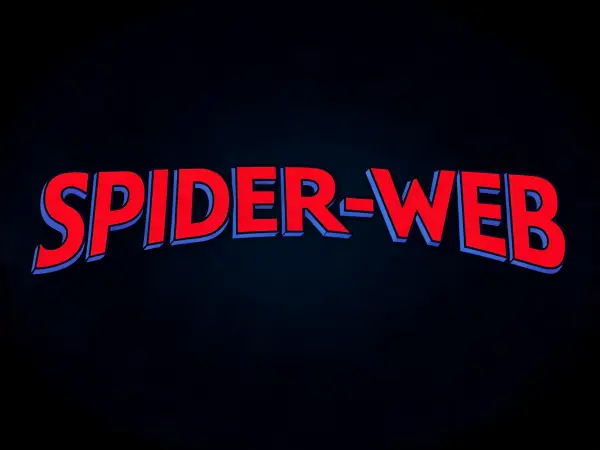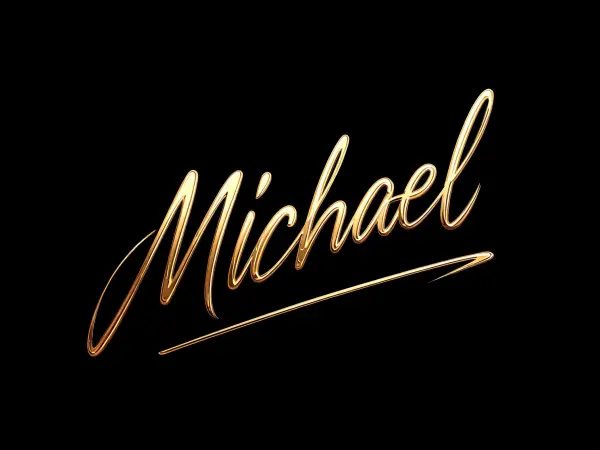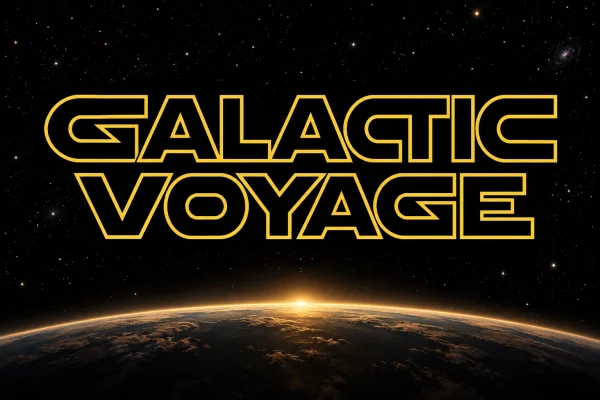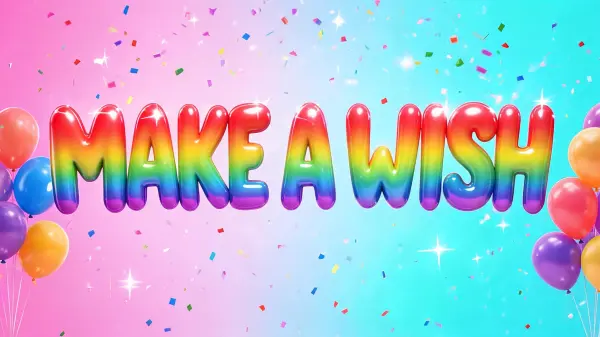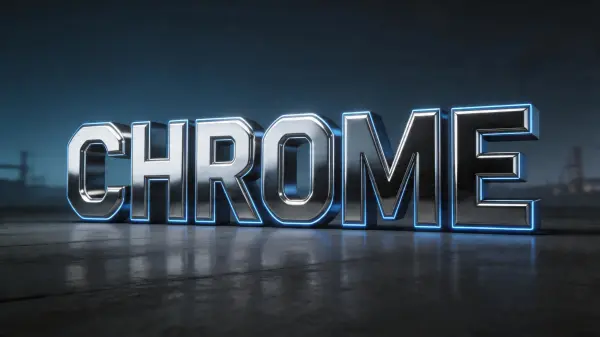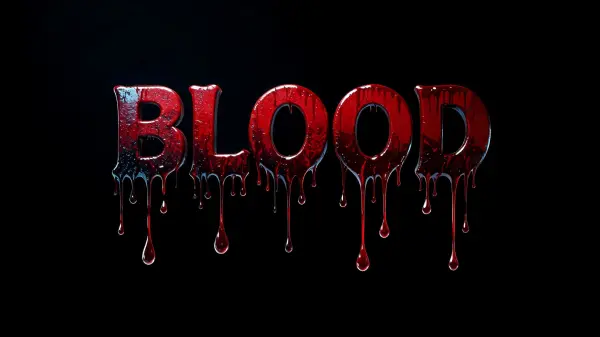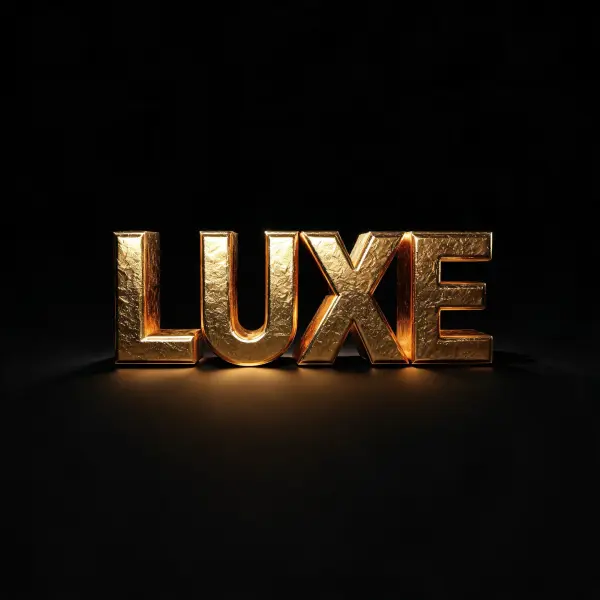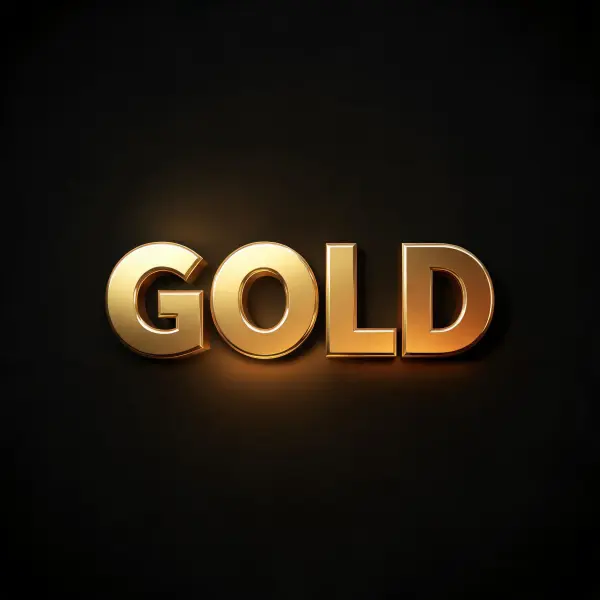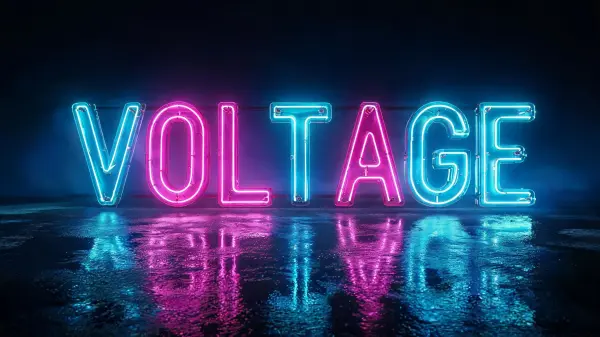
ข้อความหัวเรื่องบนโปสเตอร์
- พรอมต์หลัก
- ตัวอักษรทรงสูงแคบสีเงินปัดลาย ขอบคมชัด และเว้นระยะห่างระหว่างตัวอักษรมาก
- พรอมต์ฉาก
- พื้นหลังสีน้ำเงินเข้มพร้อมแสงนุ่มจากด้านข้าง และพื้นที่ว่างรอบข้อความหัวเรื่อง
เปลี่ยนวลีสั้น ๆ ให้เป็นภาพหัวเรื่อง เลือกสไตล์ เลย์เอาต์ และพื้นที่วาด แล้วตรวจสอบจำนวนเครดิตที่ต้องใช้ก่อนสร้าง ผลลัพธ์เป็นภาพงานศิลป์ ไม่ใช่ฟอนต์ที่ติดตั้งได้หรือข้อความที่คัดลอกได้
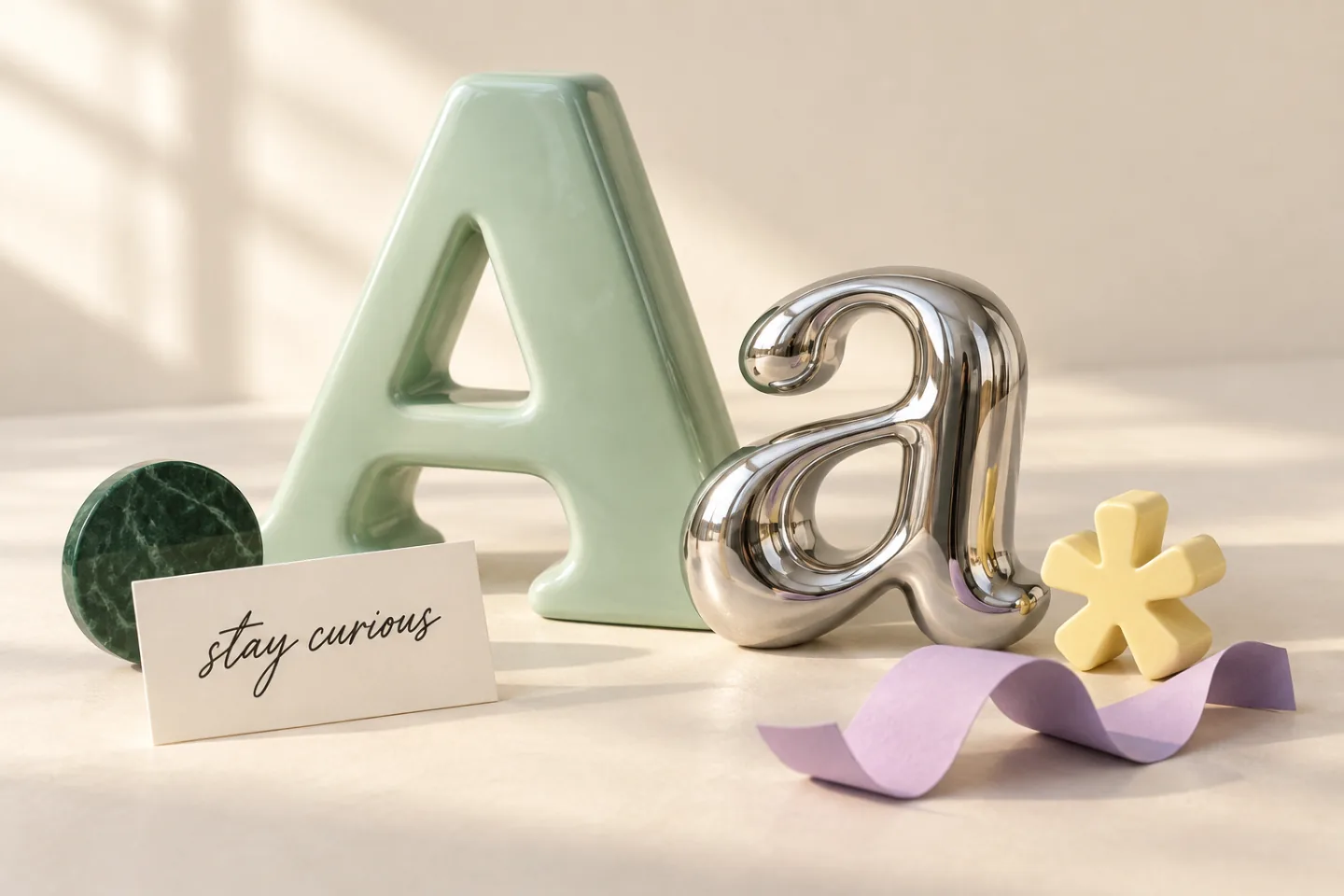
คู่มือใช้งานสตูดิโอสร้างภาพตัวอักษร
สร้างภาพหนึ่งภาพจากข้อความ รูปทรงตัวอักษร และฉากที่คุณกำหนด พื้นที่ทำงานนี้ต่อยอดจากเครื่องมือสร้างภาพแบบกะทัดรัดบนหน้าแรก โดยเพิ่มตัวเลือกการจัดองค์ประกอบภาพ ผืนผ้าใบ และการส่งออก
แยกข้อความของคุณออกจากคำอธิบายลักษณะภาพ
ใส่เฉพาะข้อความที่ต้องการให้ปรากฏใน ข้อความบนภาพ โดยไม่เกิน 64 อักขระ อธิบายรูปทรงตัวอักษร สี และวัสดุใน พรอมต์หลัก ใช้ พรอมต์ฉาก เพื่อระบุพื้นหลังและสภาพแวดล้อม
เลือกรูปทรง พื้นผิว และองค์ประกอบภาพ
แนวทางรูปแบบตัวอักษร กำหนดแนวทางรูปทรงตัวอักษร ส่วน สไตล์งานออกแบบตัวอักษร กำหนดแนวทางพื้นผิวและสภาพแวดล้อม เลือกองค์ประกอบภาพหากต้องการการจัดวางแบบเฉพาะ แล้วเลือกอัตราส่วนผืนผ้าใบให้เหมาะกับงานออกแบบ
ตรวจสอบก่อนส่งออก
ตัวอย่างคำอธิบายภาพสองแบบที่คุณปรับใช้ได้
คงชื่อเรื่องหรือชื่อของคุณเองไว้ใน ข้อความบนภาพ ตัวอย่างเหล่านี้อธิบายลักษณะที่ต้องการ ไม่ใช่ข้อความที่จะนำไปสร้างภาพ
ข้อความหัวเรื่องบนโปสเตอร์
ภาพกราฟิกชื่อ